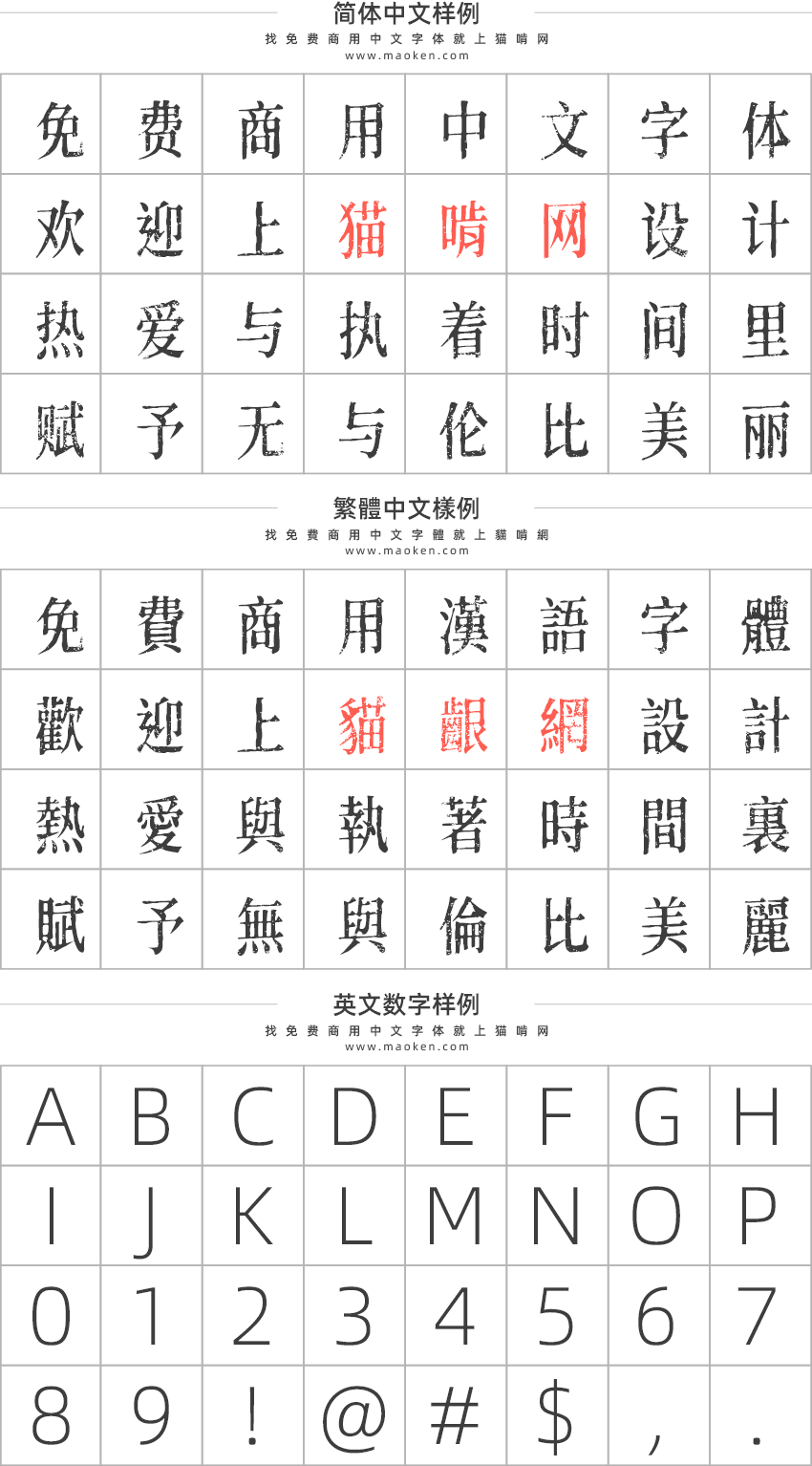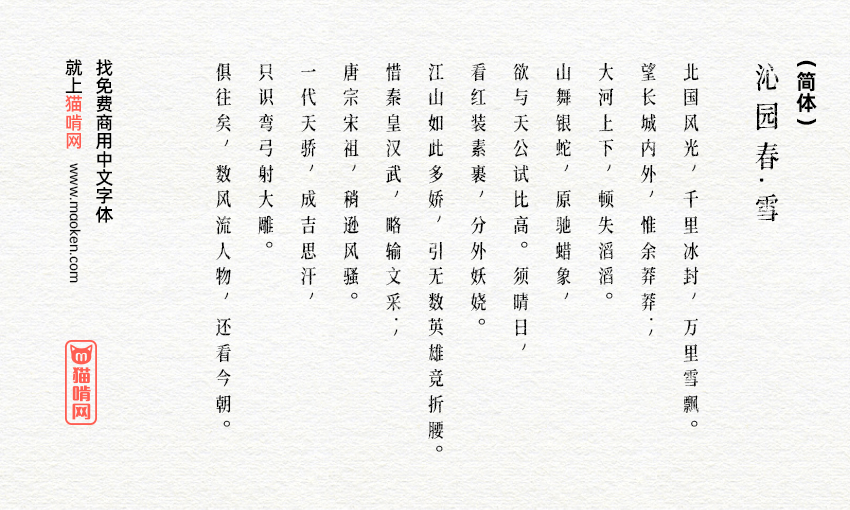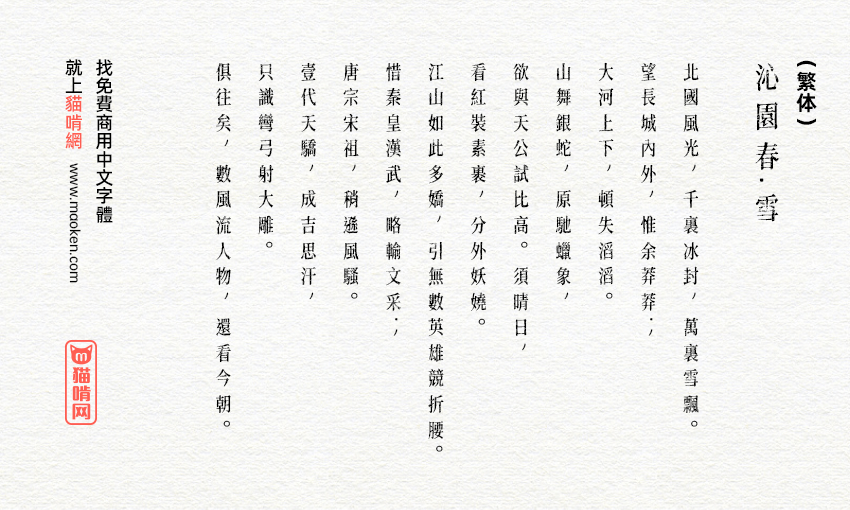
黄令东齐伋体:古典优雅媲美康熙字典体的免费商用字体
字体作者:黄令东 (中国大陆) 字体字重:1个
相信大都有听过康熙字典体,康熙字典体是文悦字库设计开发的一款古典风格字体,十分受设计师的喜爱。不过康熙字典体是收费字体,需要购买字体版权才可以使用。
现在隆重推介黄令东齐伋体,一款可以媲美康熙字典体的免费商用字体!可以免费商用!可以免费商用!黄令东齐伋体摘自明代木版印刷书籍《凌閔刻本》,采用半自动计算机视觉和OCR制作而成的一款字体。其笔画风格书法特征浓郁,比常规的明朝体更具韵律感,富有人文气息。黄令东齐伋体非常适宜用于需要展现人文感、手作感、古拙感的场景。
黄令东齐伋体是基本思源宋体改造而来,所以对中文汉字支持极佳,无论是简体还是繁体都基本上不缺字! 如果想使用古籍字形,请使用黄令东齐伋复刻体,十分漂亮的古籍字体!